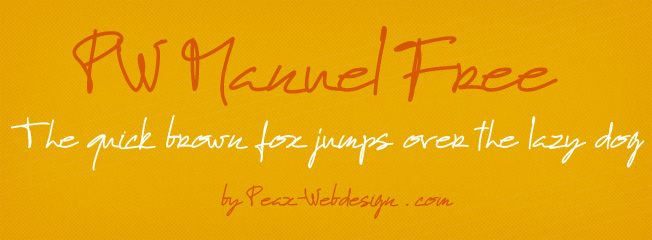
PW Manuel Free | 31 mai 2013 - Gratuit pour usage personnel et commercial
C'est une police script manuelle classique, avec un style d'écriture rapide, qui saura trouver sa place dans vos créas.